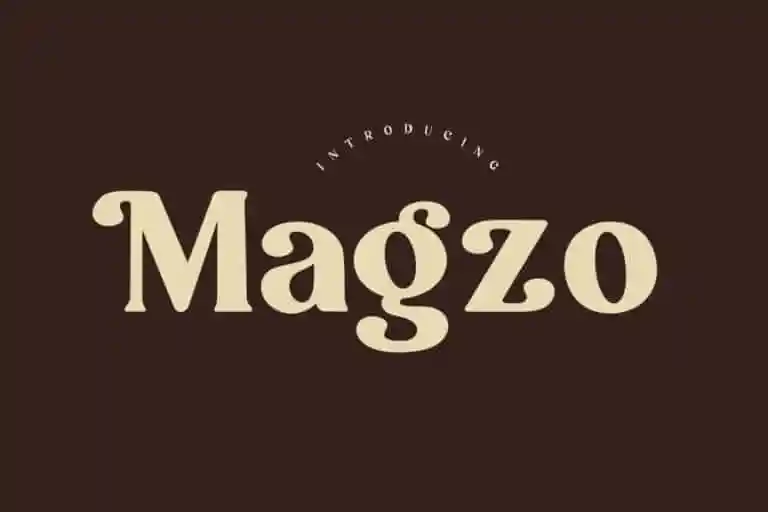
Magzo Serif Font
Magzo Serif é uma fonte séria moderna que oferece um contraste interessante com suas versões sans serif, criando visuais atraentes e sofisticados para projetos profissionais. Conhecida por seu designer HansCo na plataforma 99designs, essa fonte traz mais beleza e sofisticação aos seus trabalhos gráficos. Feita especificamente para uso em projetos de marca, impressão, casamentos e citações, Magzo Serif proporciona um toque único e encantador a cada letra. Suas linhas leves mas resistentes conferem uma elegância ao seu design. A fonte é perfeitamente adequada para uma ampla gama de aplicações, incluindo marcações, moda, templates de impressão, citações, casamentos e muito mais. Com Magzo Serif, você pode dar um toque único a qualquer projeto que esteja trabalhando, elevando-o ao próximo nível de sofisticação e beleza.